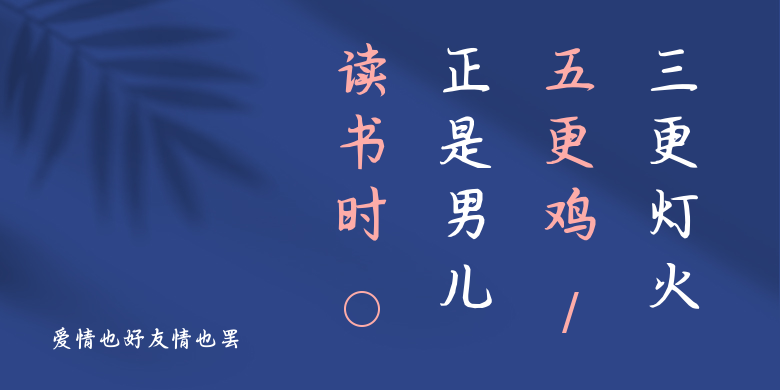
爱情也好友情也罢
爱情也好友情也罢,这款字体结构工整、笔画清晰,兼顾美观与易读性,适用于标题、正文、海报、包装、LOGO 等多种场景。字形优雅稳定,风格百搭耐看,适配日常排版与创意设计,让文字呈现更舒适、更具质感。爱情也好友情也罢一笔一画,皆是细节,以均衡的比例、流畅的线条打造舒适视觉体验,字形端正大气,风格简约现代。无论是商业设计、品牌宣传还是日常排版,都能轻松驾驭,让文字更有格调与力量。爱情也好友情也罢字体下载。